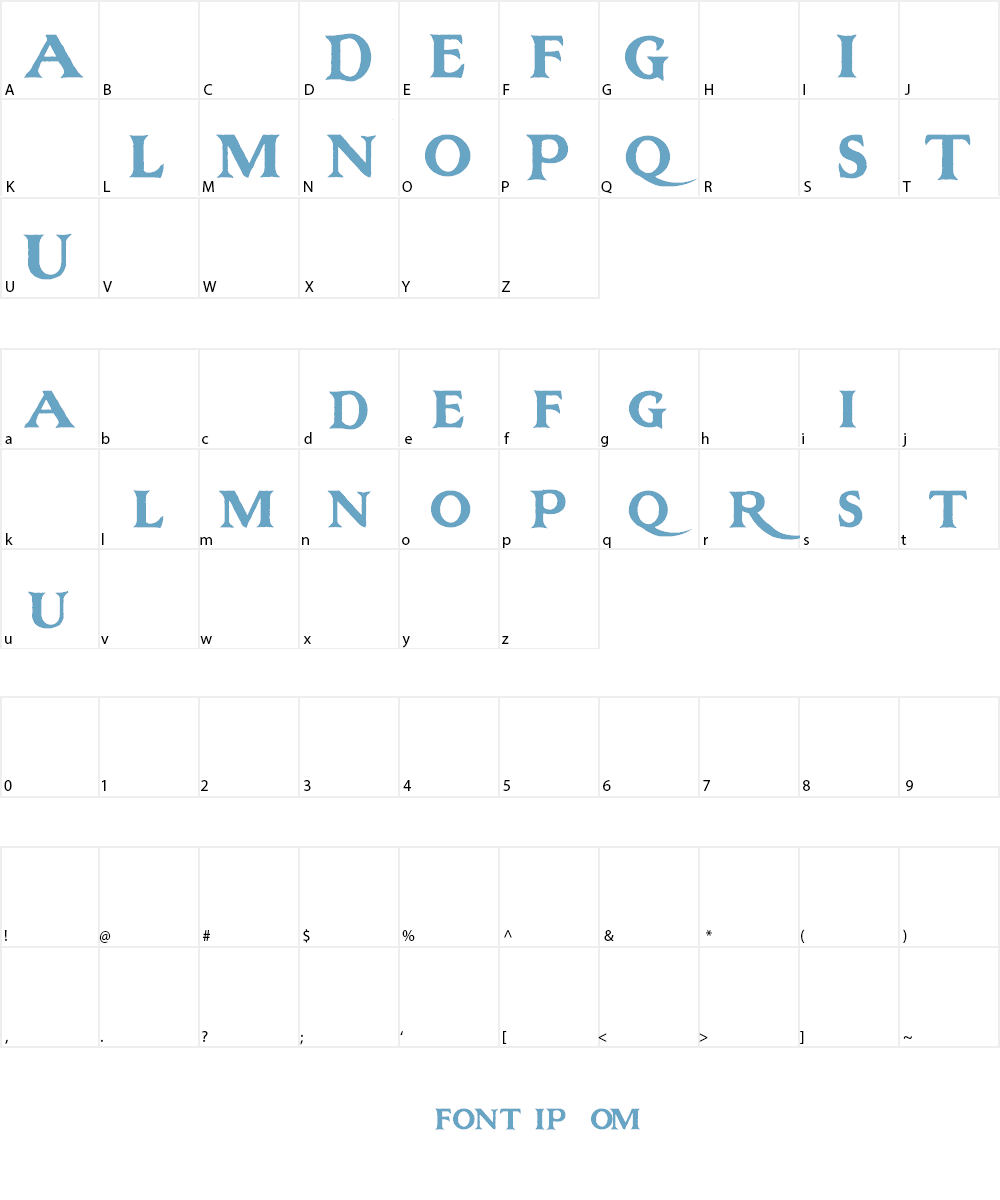
Un FAN-MADE de la película "PETE'S DRAGON / MI AMIGO EL DRAGÓN" de Disney.
PRÓXIMAMENTE, NUEVAS ACTUALIZACIONES CON LA FONT CON ESTOS:
. . : , - ! " # $ % & /()=?¡ y números 0123456789
PRÓXIMAMENTE, NUEVAS ACTUALIZACIONES CON LA FONT CON ESTOS:
. . : , - ! " # $ % & /()=?¡ y números 0123456789